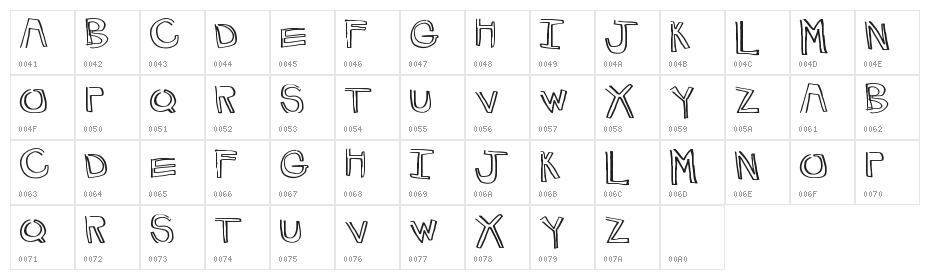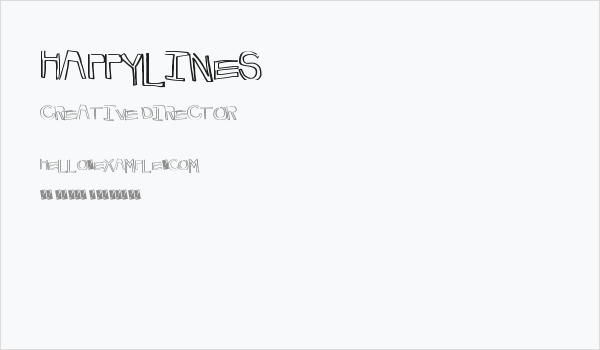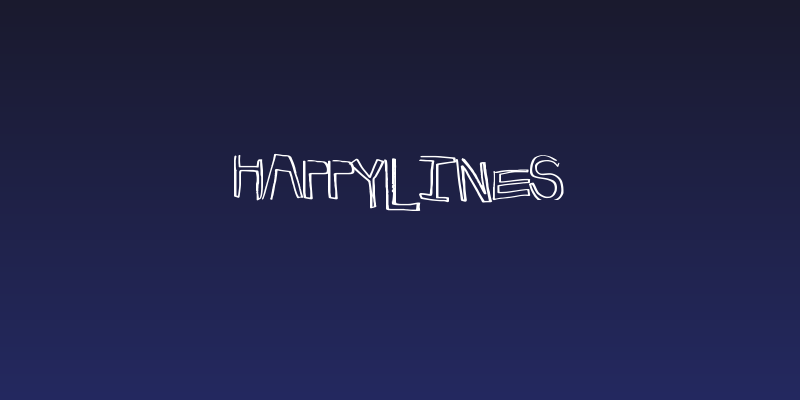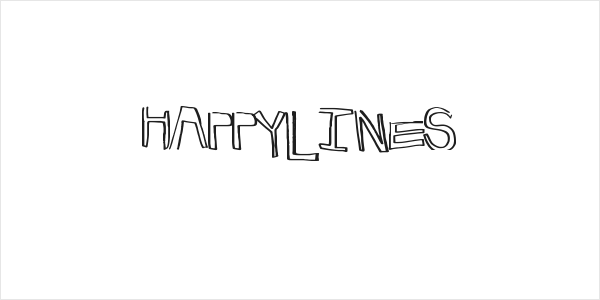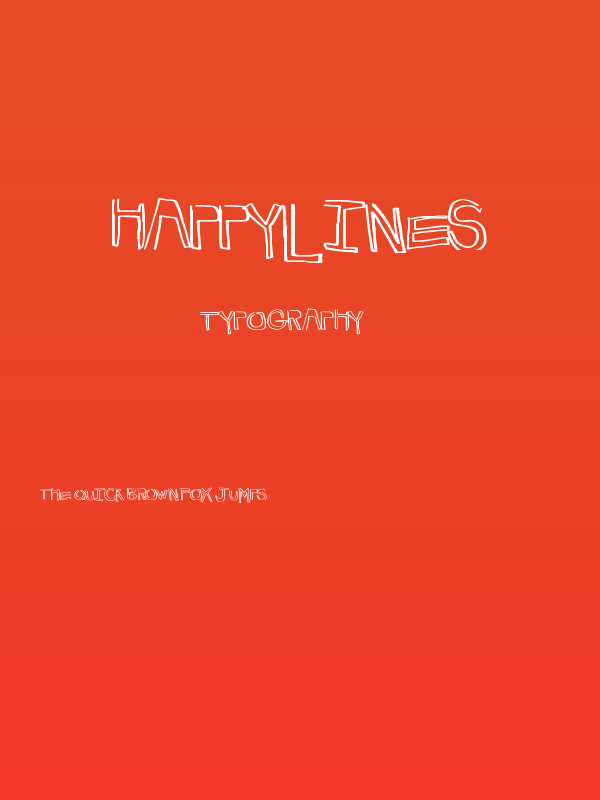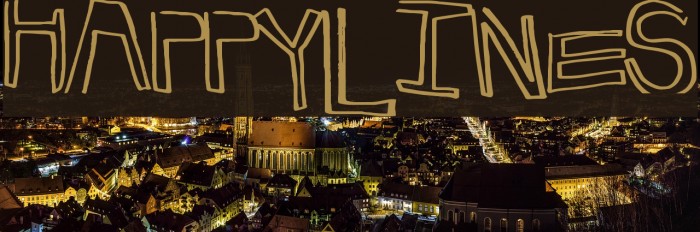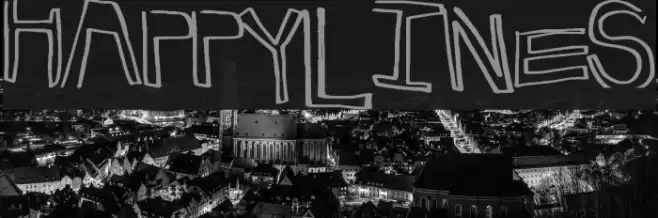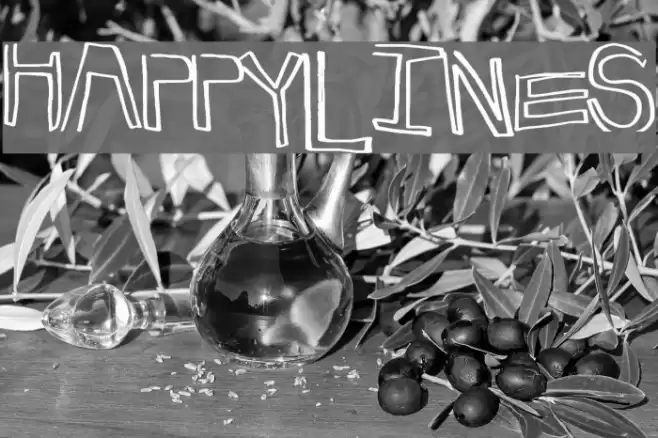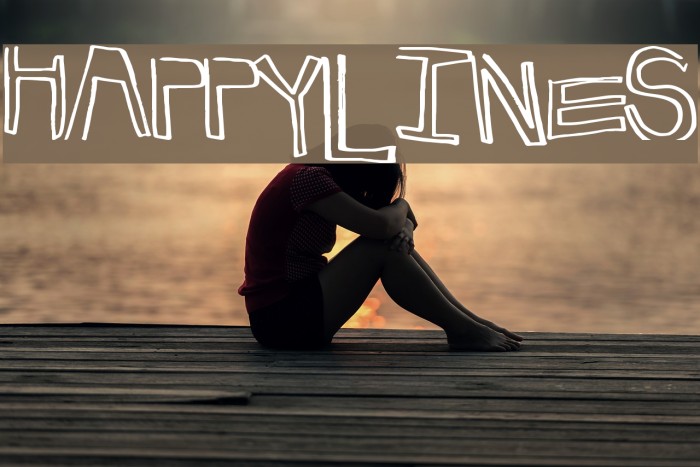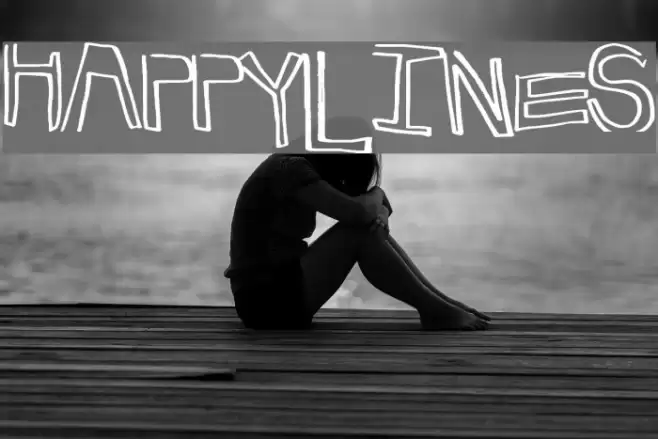
HappyLines Font
| Gesamtstil | Whimsical |
| Anwendungsfall | Headlines, Posters, Creative projects |
| Vorgeschlagene Projekte | Ideal for children's books, comic strips, playful branding, and creative posters. |